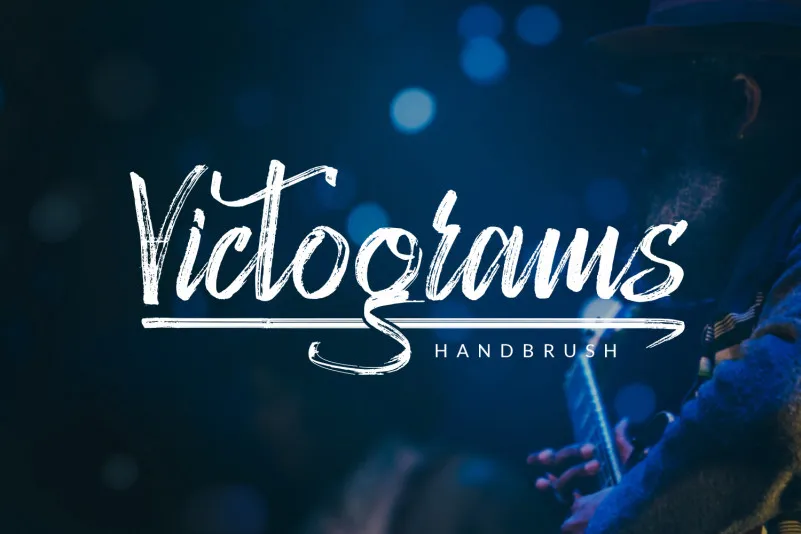
Victograms Handbrush Font – Download Grátis
A Victograms Handbrush Font é uma elegante tipografia para canetas a mão projetada especialmente para aqueles que buscam um toque refinado e autêntico nas criações digitais. Esta fonte de brush é perfeita para uma variedade de projetos, desde identidades visuais criativas até peças de design do lar e embalagens de produtos. Também se destaca na criação de arte para mugs, cartões de lembrança, capas de livros e outras mensagens que requerem um toque personalizado. Com sua versatilidade e beleza natural, a Victograms Handbrush Font é perfeita tanto para quem busca uma expressão artística quanto para aqueles buscando criar algo único ou simplesmente desejam dar um toque especial aos seus trabalhos. Seja você criando materiais de embalagem, arte digital, artefatos pessoais ou até mesmo mensagens em papel – a Victograms Handbrush Font será sua escolha perfeita.